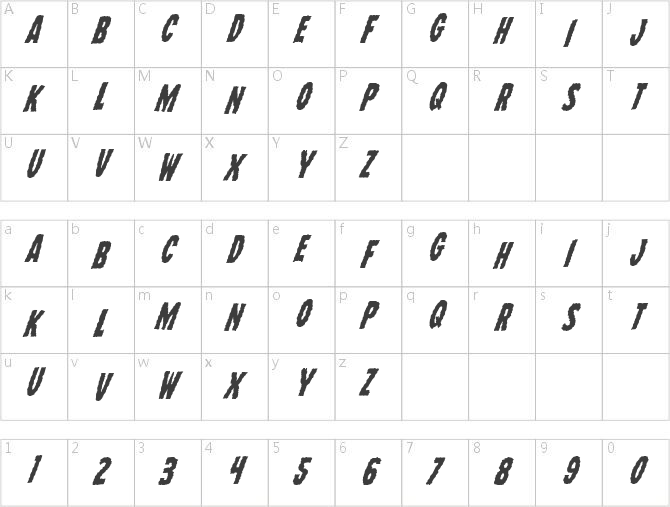
wolfbrotherssuperital 詳情頁
wolfbrotherssuperital字體字庫是一款讓人賞心悅目、百看不厭的英文字體,適合各類廣告和產(chǎn)品包裝設(shè)計應(yīng)用,字體大小0.15MB,格式為ttf字體,上傳用戶是rose,作者/版權(quán)方為未知